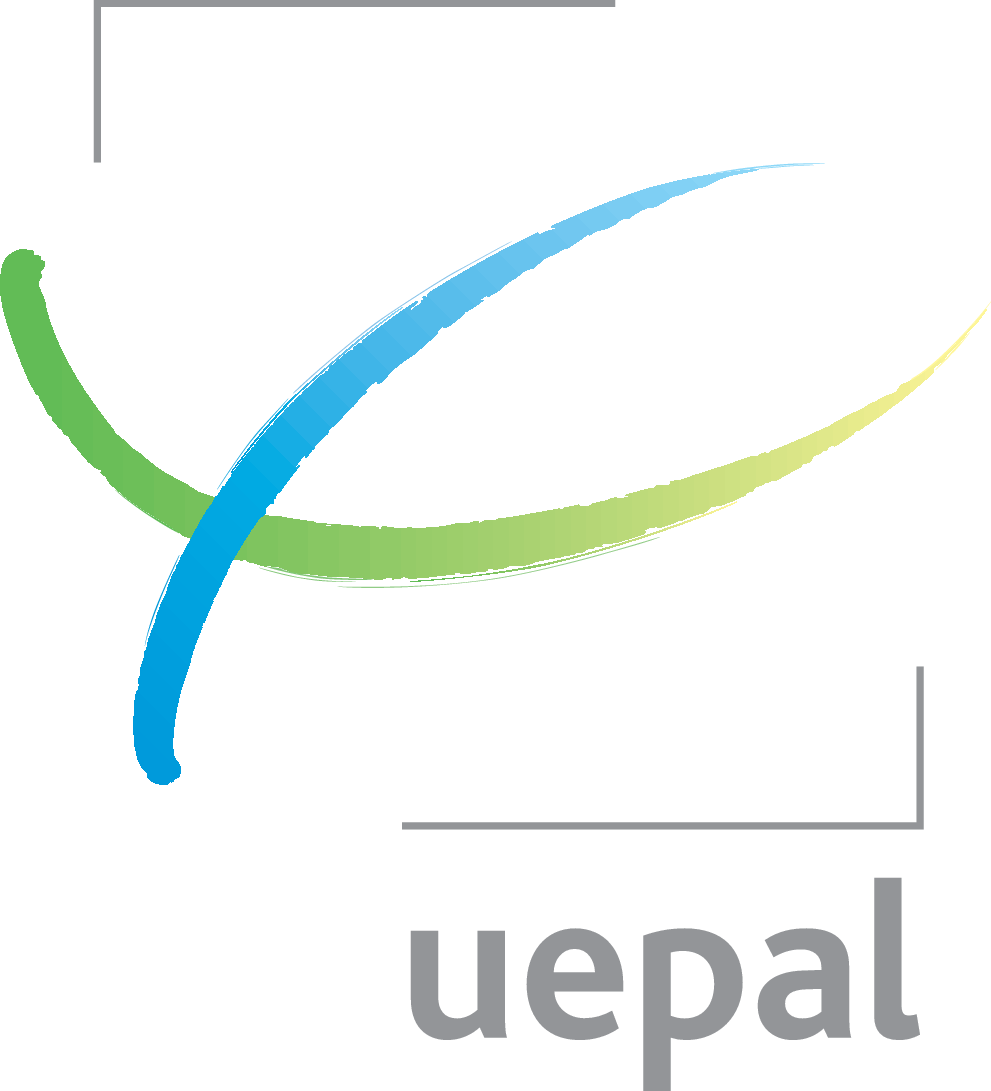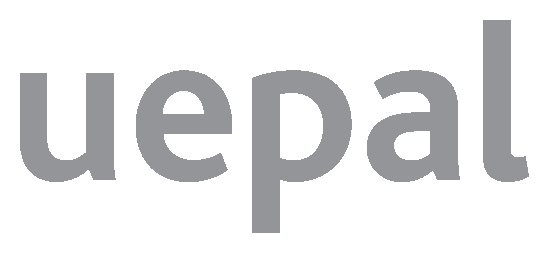
Schrift in Uepal-Logo, humanistische Serifenlose
Wüsste jemand, welche Schrift in dem Logo der ev. Kirche in Elsass-Lothringen (UEPAL) verwendet wurde? Eigene Recherchen und WhatTheFont ergaben bisher nichts. Ich dachte zuerst an eine Schrift von Dalton Maag oder Font Smith, was aber nicht zutrifft.
Ich wage zu behaupten, dass das p konstruiert oder von einer anderen Schrift »geborgt« wurde. u, e, a und l sehen sehr nach Source Sans Pro aus, das p eher nach der Ubuntu.
Bei stringenter Konstruktionsweise der Buchstaben sollte das p zumindest nicht diese Form haben. — Aber da wissen die Spezialisten hier bestimmt viel genauer Bescheid.